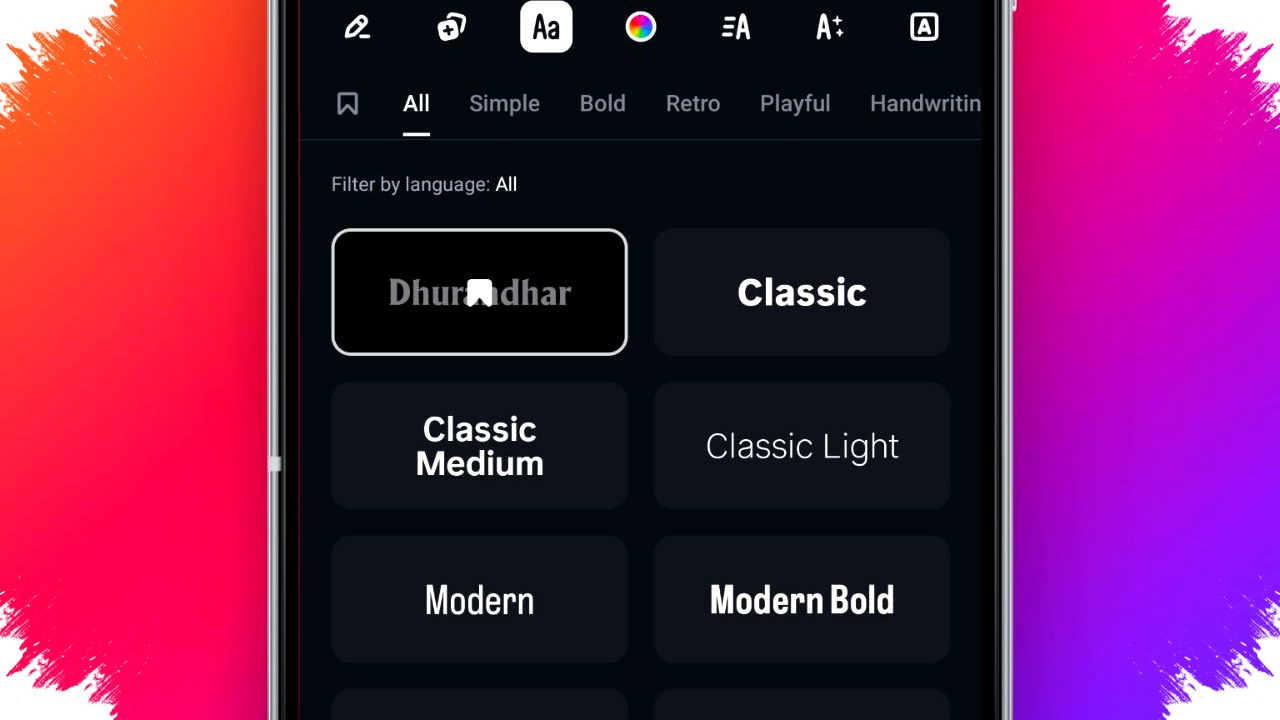
Instagram menambah opsi font baru di aplikasi Edits dengan gaya visual yang terinspirasi dari “Dhurandhar 2”. Fitur ini ditujukan untuk kreator Reels yang ingin memberi teks bergaya sinematik pada video tanpa perlu aplikasi tambahan.
Font tersebut tidak hadir permanen. Instagram memastikan opsi ini dirilis untuk waktu terbatas di Edits versi Android dan iOS, sehingga pengguna yang ingin mencobanya perlu memanfaatkan fitur itu sebelum ditarik dari aplikasi.
Font sinematik baru di Instagram Edits
Berdasarkan informasi dari artikel referensi Beebom, font baru ini mengambil inspirasi dari tipografi tebal yang identik dengan materi promosi dan sekuens judul film “Dhurandhar: The Revenge”. Pendekatan visual itu membuat overlay teks terlihat lebih dramatis dan menyerupai gaya judul film aksi.
Kehadiran font bertema film ini menunjukkan strategi Instagram yang makin agresif dalam menghadirkan alat kreatif berbasis tren. Langkah tersebut juga memperkuat posisi Edits sebagai aplikasi edit video yang ingin bersaing langsung dengan layanan seperti CapCut.
Instagram belum mengungkap tanggal pasti kapan font ini akan dihapus. Namun, statusnya sebagai fitur sementara mengindikasikan adanya kaitan promosi dengan momentum popularitas waralaba film tersebut.
Dalam konteks produk, keputusan menghadirkan elemen visual yang relevan dengan budaya pop bukan hal baru di platform media sosial. Format seperti ini biasanya dipakai untuk meningkatkan partisipasi kreator saat topik hiburan tertentu sedang ramai dibicarakan.
Cara memakai font Dhurandhar di Instagram Edits
Penggunaan font baru ini terintegrasi langsung ke alur edit yang sudah ada di aplikasi Edits. Artinya, pengguna tidak perlu memasang plugin atau paket font terpisah.
Berikut langkah yang disebut dalam referensi:
- Buka aplikasi Edits di ponsel.
- Buat Reel baru atau buka draft yang sudah ada.
- Masuk ke menu teks atau pilihan font.
- Cari font yang terinspirasi “Dhurandhar”.
- Tambahkan teks, atur tampilannya, lalu pratinjau video.
- Publikasikan Reel jika hasilnya sudah sesuai.
Langkah tersebut berlaku untuk perangkat Android maupun iOS. Selama fitur masih aktif di akun dan versi aplikasi yang dipakai, opsi font akan muncul bersama pilihan font lain di editor teks.
Jika font belum terlihat, pengguna dapat memeriksa pembaruan aplikasi di toko aplikasi resmi. Peluncuran fitur seperti ini sering dilakukan bertahap, sehingga ketersediaannya bisa berbeda antarperangkat atau wilayah pada waktu yang sama.
Apa yang membuat font ini menarik
Daya tarik utamanya ada pada karakter huruf yang tebal dan bernuansa film. Gaya seperti ini cocok untuk membuka video, menandai adegan penting, atau menambahkan judul pendek yang ingin langsung mencuri perhatian penonton.
Bagi kreator Reels, pemilihan font sering berpengaruh pada kesan visual dalam beberapa detik pertama. Di format video vertikal yang serba cepat, teks yang kuat dan mudah dibaca bisa membantu menaikkan peluang penonton bertahan lebih lama.
Font bertema sinematik juga relevan untuk konten hiburan, fan edit, trailer pendek, atau video dengan tone dramatis. Namun, efektivitasnya tetap bergantung pada kecocokan dengan warna, durasi kemunculan teks, dan komposisi visual video.
Sifatnya terbatas, pengguna perlu bergerak cepat
Salah satu hal terpenting dari pembaruan ini adalah statusnya yang sementara. Beebom melaporkan bahwa Instagram sudah mengonfirmasi peluncuran terbatas tersebut, meski belum memberi tenggat pencabutan yang spesifik.
Karena belum ada tanggal resmi, peluang terbaik bagi pengguna adalah mencoba fitur ini sesegera mungkin. Jika menunggu terlalu lama, font bisa saja hilang ketika kampanye promosi film sudah berakhir atau setelah masa tayangnya selesai di bioskop.
Bagi kreator yang ingin memanfaatkan tren, waktu menjadi faktor penting. Konten yang mengangkat elemen visual yang sedang ramai biasanya memiliki peluang lebih besar untuk menarik perhatian audiens di feed maupun Discover.
Edits makin diposisikan sebagai alat kreator
Edits sendiri terus berkembang sebagai pusat pembuatan konten singkat di ekosistem Instagram. Penambahan font tematik menunjukkan bahwa aplikasi ini tidak hanya berfokus pada fungsi edit dasar, tetapi juga pada alat ekspresi yang mengikuti tren populer.
Strategi ini sejalan dengan kebutuhan kreator yang menginginkan proses produksi cepat dalam satu aplikasi. Dengan menyediakan font khusus, Instagram berupaya menahan pengguna agar tetap membuat, mengedit, dan memublikasikan konten tanpa keluar dari platformnya.
Di sisi lain, fitur semacam ini juga menguntungkan dari sudut pemasaran digital. Kolaborasi visual dengan tema film dapat mendorong percakapan organik, terutama saat penggemar mulai memakai gaya yang sama pada banyak unggahan Reels.
Untuk pengguna yang ingin mencoba, syarat utamanya cukup sederhana: pastikan aplikasi Edits sudah diperbarui dan cek menu font saat mulai mengedit Reel. Selama opsi itu masih tersedia, font “Dhurandhar 2”-inspired dapat langsung dipakai untuk memberi sentuhan judul yang lebih tegas, dramatis, dan selaras dengan tren visual yang sedang diangkat Instagram.